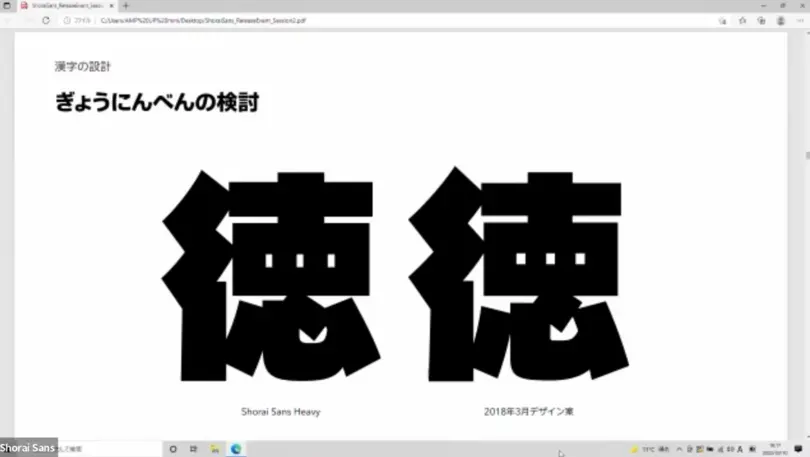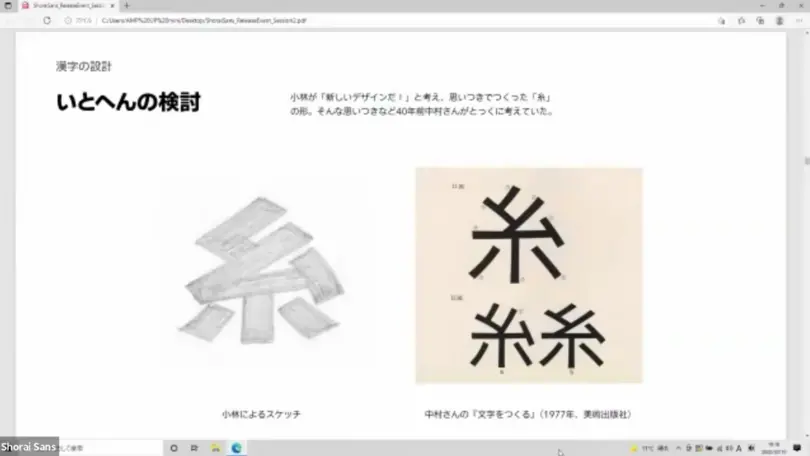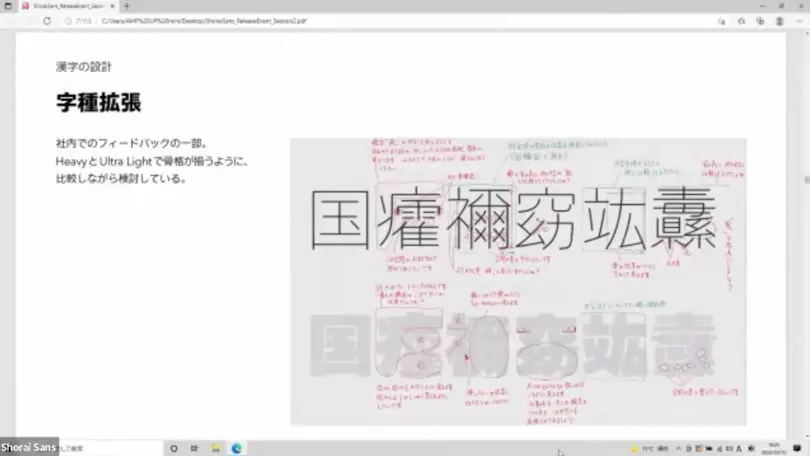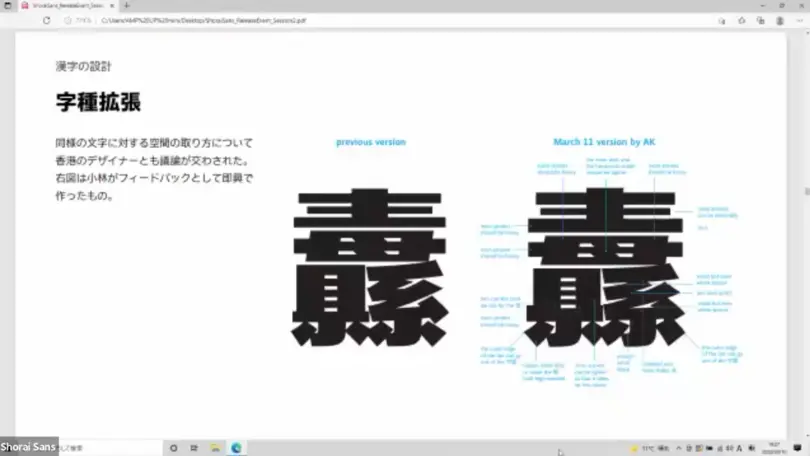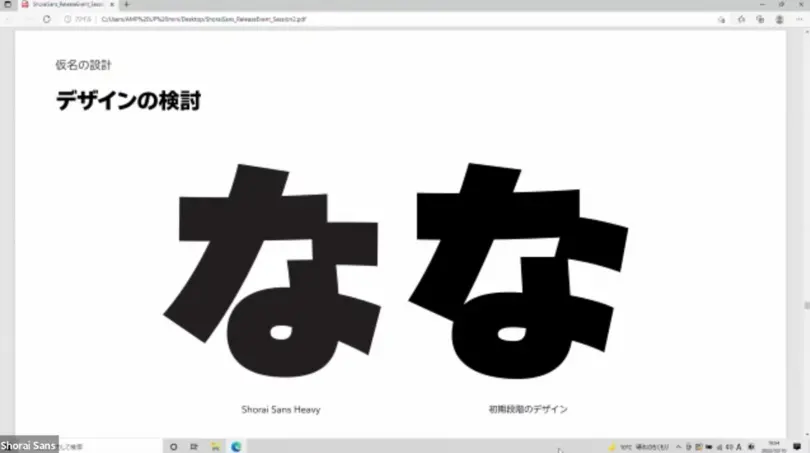
Shorai Sans のデザインを担当した3名によるトークセッション
Monotype の小林と土井が中村征宏氏をゲストスピーカーに迎え、Shorai Sans 制作メンバーでトークセッションを行いました。中村氏は、1970年代から本格的に書体デザインを始め、ナールやゴナなどの有名和文書体をデザイン。半世紀にわたり、書体を作り続けている第一人者です。
2022年2月にリリースされた Monotype の和文書体 Shorai Sans。Avenir Next にあわせて開発された、すっきりと読みやすい和文書体です。書体の発売を記念して、オンラインのトークイベントが開催されました。
このトークイベントでは、書体制作にかかわった Monotype クリエイティブ・タイプディレクターの小林章、Monotype シニア・タイプデザイナーの土井遼太が登壇。ゲストスピーカーとして、Shorai Sans の見本帳デザインを担当した祖父江慎氏、Shorai Sans の書体デザインに携わった中村征宏氏を迎えて、2つのセッショントークが行われました。
Shorai Sans の特徴とコンセプト
定番の欧文書体を数多く所有している Monotype で和文書体を作るならば、欧文書体にあわせた和文書体を作ろうということになり、2017年に Neue Frutiger にあわせた和文書体、たづがね角ゴシック体を発表。それに続く和文書体として、Avenir Next にあわせた和文書体を開発することになりました。
Avenir Next は、 Adrian Frutiger(アドリアン・フルティガー)氏が作った欧文書体 Avenir の改刻・字種拡張版で、ジオメトリックでありながらも、小文字aとoの読み間違いがないようデザインされ、可読性にも配慮されています。Avenir Next の10種類の太さにあわせて、和文書体も10種類の太さが作られました。
「何も足さない素のかたち」というキャッチフレーズのとおり、文字の形は単純明快。幾何学的でありながら、人が手で書いたような雰囲気がある書体です。
漢字の設計
極太のウェイトは、限界プラス1割の太さまで太くされており、漢字はたづがね角ゴシックの一番太いウェイトより太くなっています。
文字を太くしようとすると線の太さが均等になりがちで、どこを太くしてどこを細くするかバランスが難しいと言います。例えば、「鳴」という漢字では、口へんの左側の縦棒と「鳥」の縦棒を思い切って太くすることで全体を太く見せています。
また、「長」では一番上の横線と中央の長い横線を太くし、その間の線は細いままで、全体を太く表現。横線が並ぶ漢字では、このように太細の緩急をつけて処理しました。
「徳」のぎょうにんべんは、1画目と2画目を離すと線の角が全部見えてしまうため、1画目と2画目をくっつけて、なるべく単純な形に。3画目もくっつけると真っ黒なかたまりになってしまうため、始筆部の右上を離しています。小林が日本で習っていた寄席文字でもこのような処理の仕方をするそうです。
「糸」の斜め線の角度をどうするかも検討。小林が鉛筆でスケッチした「糸」の形は、中村氏が40年前にすでにいくつか考えていたものに近いことがわかりました。正解は一つではないので発想を膨らませて、いろいろ検討してみることが大切と小林は言います。
漢字は文字数が多いため、最初にサンプルで何文字か作り、他の文字にも字種拡張していきました。画数が多い文字、少ない文字で10ウェイトを作り、他の文字に展開していけるかを検証。中村氏、小林、土井で方針を決め、その方針で他の文字を作ってもらうよう他のデザイナーに指示しました。
最も細い Ultra Light と 最も太い Heavy の文字を並べて作り、太いウェイトと細いウェイトで整合性が取れているか、同じ書体に見えるかも検証。画数が非常に多い文字を太くする場合は、いかに極太の字に見せるかが難しいところ。例えば、「纛」(はたぼこ)という文字では、Monotype 香港のデザイナーが作った漢字に対して、小林が英語で指示を書き込み、修正点を伝えました。漢字の字種拡張では、日本のデザイナーだけでなく、中国、香港のデザイナーとコラボレーションしました。
2019年、香港の Monotype に中村氏、小林、土井が出張し、現地のデザイナー、エンジニアとワークショップを実施。デザインができてからエンジニアに渡すのではなく、デザインの途中からエンジニアが加わって、一緒に制作。日本とドイツからもスタッフが参加し、国境を超えたコラボレーションになりました。
書体開発の初期段階では、愛知県にある中村氏のアトリエに小林、土井、エンジニアが集まり、3日間ずつ10回、のべ30日間のワークショプを実施。2018年から書体の開発を始め、順調に進んでいましたが、2020年はコロナの影響で中村氏のアトリエでの共同作業が不可能に。以降、小林がドイツからオンラインで参加し、リモートで開発を進めることになりました。
仮名の設計
Shorai Sans は、ジオメトリックでありながら、手書きの雰囲気も残しており、仮名では「き、お、す、な」にその特徴が表れています。
「き」は、細いウェイトでは3画目がつながっていますが、太いウェイトでは離れています。太いウェイトで3画目をつながったままにすると、つながりの部分の線が細くなってしまうため、線の太さを保つためにそのような処理をしたと中村氏は言います。
「な」は、2画目の終筆部を結びの部分にくっつけるか、くっつけないかを検討。また3画目を水平にするか、斜めにするかも検討しました。
[世代も国境も超えたコラボレーション]
1988年にスイスの Adrian Frutiger 氏が Avenir を設計。6ウェイトありましたが、太さの差があまりありませんでした。その後、2002〜04年に Frutiger 氏と小林が Avenir Next を制作。極細から極太まで太さに差をつけた6ウェイトのファミリー構成に変更されました。
2020年に Avenir Next World を作る際に Avenir Next を10ウェイトに拡張。そして、その10ウェイトにあわせて、2022年に Shorai Sans が完成。つまり、最初の Avenir から Shorai Sans まで、国境を超えて34年かかったことになります。
また、中村氏、小林、土井の3世代が関わったことにより、Shorai Sans の制作は世代も超えたコラボレーションになりました。
Q & A
質問:開発の中で何が一番刺激になったか?
中村氏:小林さんのフィードバックが厳密でした。40文字を完成させるのに5回のフィードバックがあり、自分がちゃんとやっていけるのかと思うくらい驚き、また刺激にもなりました。私が写植の書体を作っていた頃、修正は1回でしたから、5回というのは大変びっくりしました。
質問:写植時代からデジタルフォントの時代への変化をどのように捉えているか?
中村氏:大きな違いは、作る技法ですね。手書きか、マウスか。イメージした文字を作るという点ではどちらでも同じだと思います。
小林:写植時代は、作った書体を写植で打って検証できるようになるまで、1か月以上かかっていましたが、今はデジタルですぐ直せるようになりました。写植時代は1書体作ってから違う太さの書体を作るのに1年以上かかっていたんです。今は、太いウェイトと細いウェイトの中間のウェイトを作る時にコンピュータを使えるようになったことが大きいです。一度に10ウェイトを発表するのは昔なら考えられませんでした。
質問:線の「太い・細い」のバランスを他の人にどう伝えるのか?
小林:私が指示を出しますが、1回ではうまく伝わりません。普通のゴシックと Shorai Sansがどう違うのかを理解してもらうまでに時間がかかりました。
土井:自分は小林さんから指示を受ける側であり、香港のデザイナーに英語で指示を出す側でもあるので、小林さんの意図を正確に理解できていないと英語で指示ができません。中村さんや小林さんに何度も質問して自分の中で咀嚼してから指示を出していました。
質問:よい書体の定義とは?
中村氏:一概に「よい書体はこれです」と限定できません。使用目的によって、よい書体は変わります。目的にあわせて何種類か候補を出して、その目的にあったものがよい書体だと言えるのではないでしょうか。
質問:今回のプロジェクトについて
中村氏:この書体は一時的に使われるのではなく、50年、100年、長い時間、広く使われる書体になると思います。
小林: Frutiger さんと Avenir Next を作っていた頃はそれにあう和文書体を作ることは考えてもいませんでした。その後、自分が憧れていた中村さんとこの書体を作ることができたのは、大きな物語のような気がします。長く使われる書体になってほしいです。